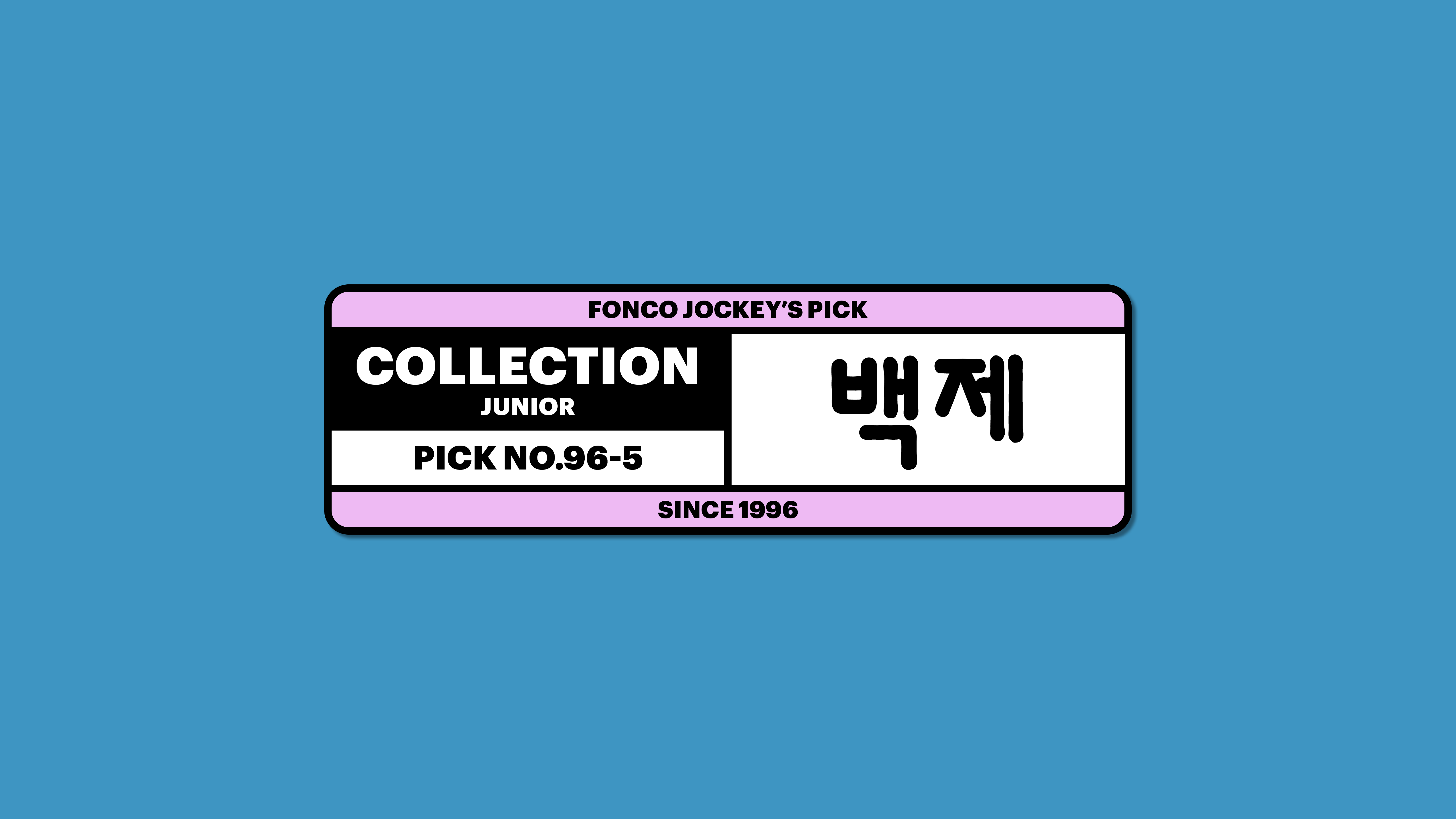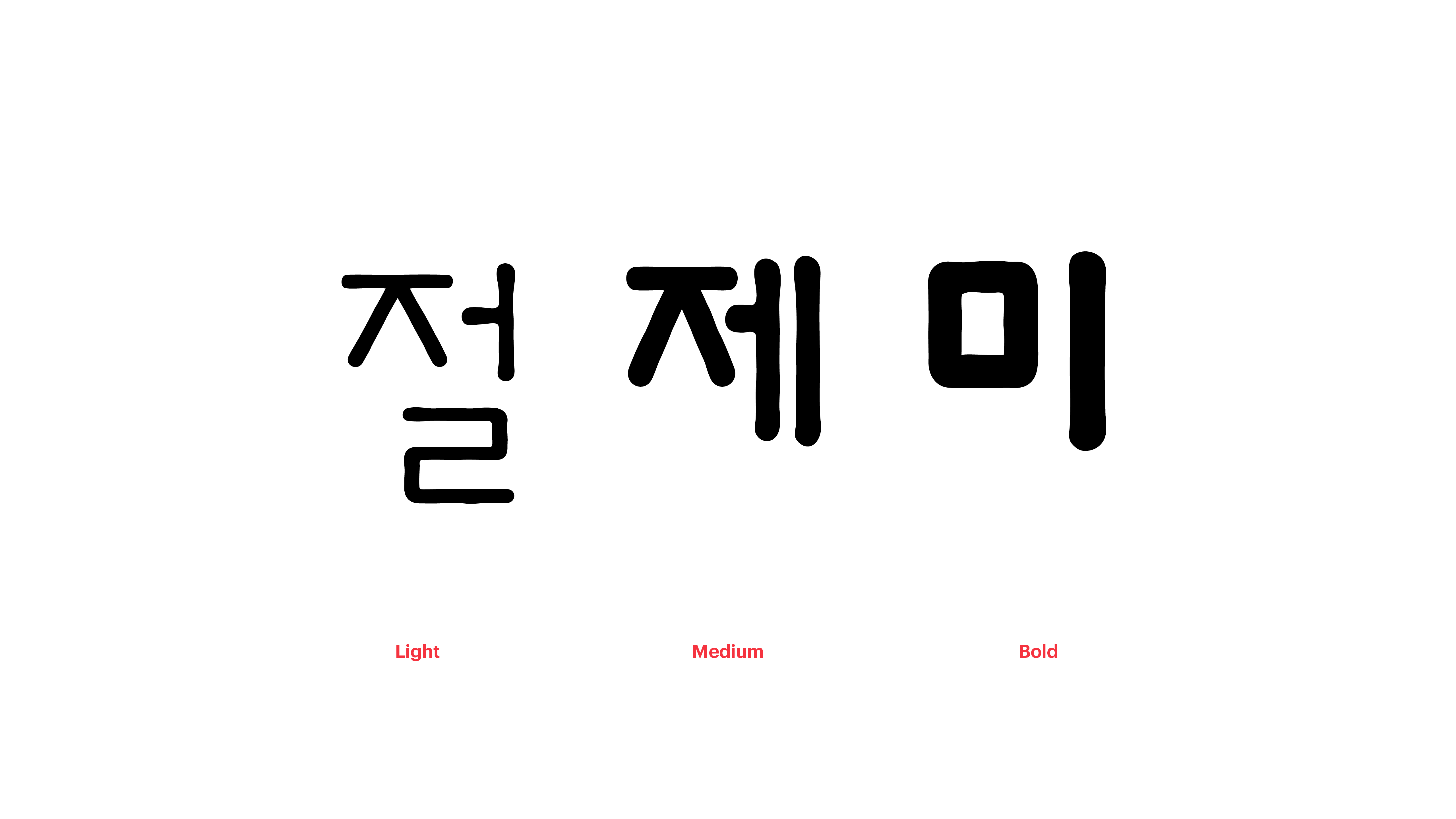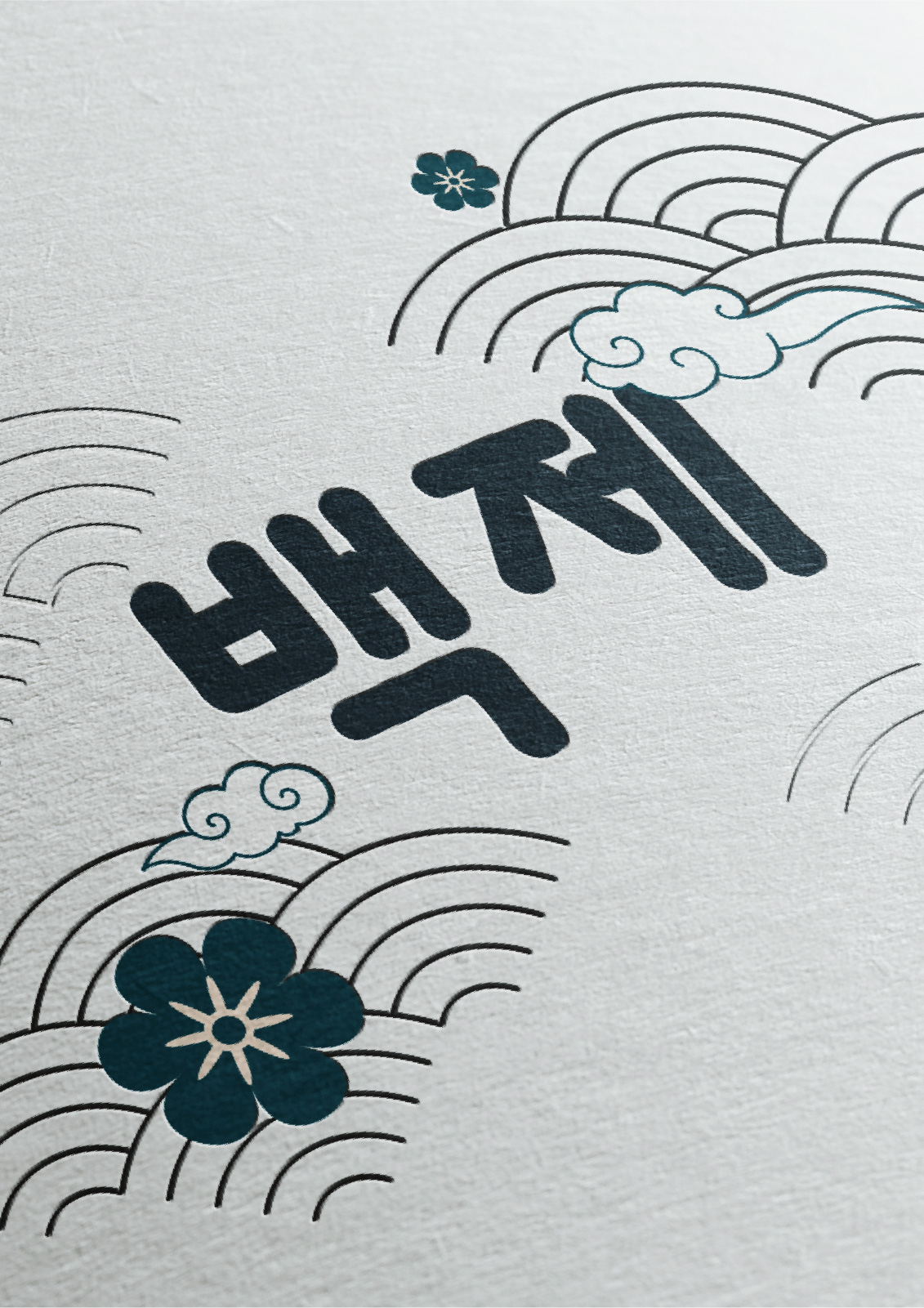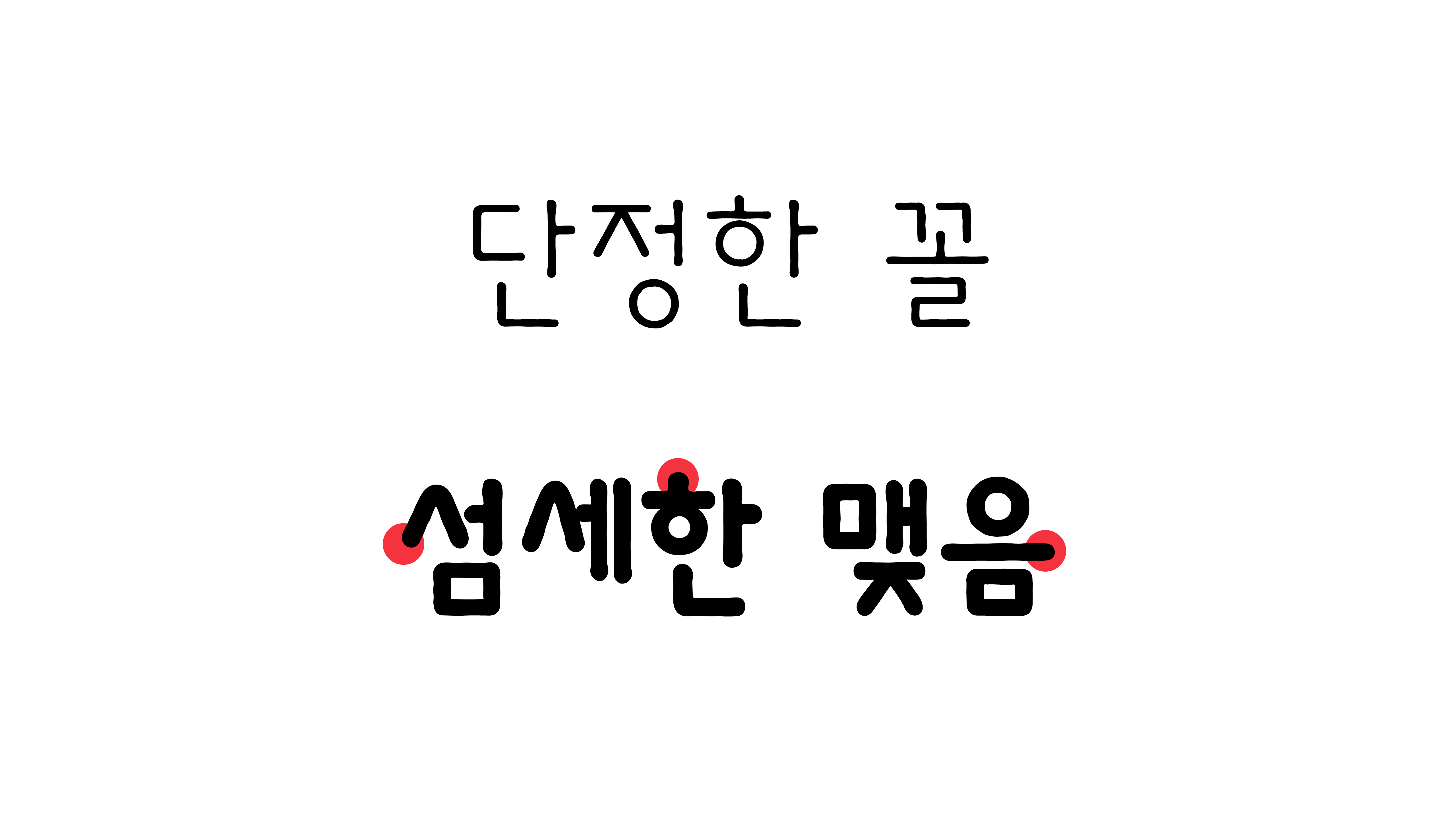
백제
Yoon 백제
천천히 방안을 가득 매우는 난향과 같이, 곱씹을수록 배어나오는 은은한 멋. 백제 문화의 정수를 담아내고자 한 폰트입니다. 단정하고 기본적인 꼴에 돌기, 맺음을 섬세하게 표현하여 개성을 더했고, 보면 볼수록 세련된 멋이 느껴질 수 있도록 섬세한 디테일의 표현에 집중하였습니다.